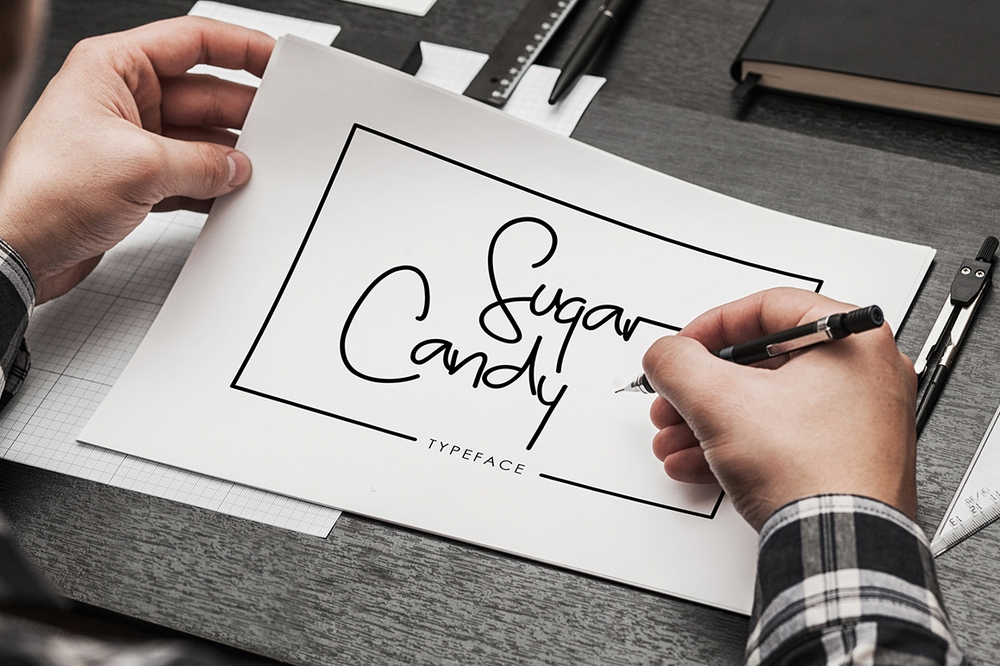
Sugar Candy Signature Font
Introduzimos a Sugar Candy Signature Font! Desenhada por madeDeduk, esta é uma fonte premium que pode ser encontrada no fontbundles. Infelizmente, hoje você poderá baixá-la gratuitamente. A Sugar Candy está inspirada em estilos de escrita clássica e foi projetada para criar qualquer tipo de marca, embalagem de produto, convite, citações, camisetas ou até mesmo cartazes. Seja ela a solução perfeita para estilizar seus materiais digitais com um toque elegante e sofisticado. Esta fonte é especialmente adequada aos designers que valorizam uma escrita à mão realista, que pode ser usada em qualquer aplicação visual de texto. O uso da Sugar Candy será a garantia de uma identidade visual única e memorável para seus projetos.